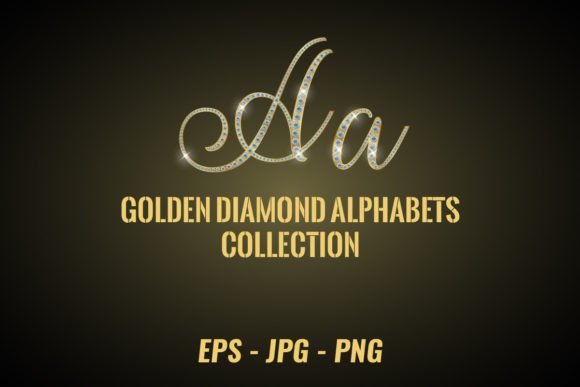
Diamond Uppercase and Lowercase Pack
Diamond Uppercase and Lowercase Packμ κ°μ κ³ νμ§ μμ°μ μ°Ύκ³ μλ€λ©΄ μ΄ ν리미μ ν¨ν€μ§λ μ°½μμ μΈ νλ‘μ νΈλ₯Ό μν νμμ μΈ μ νμ λλ€.